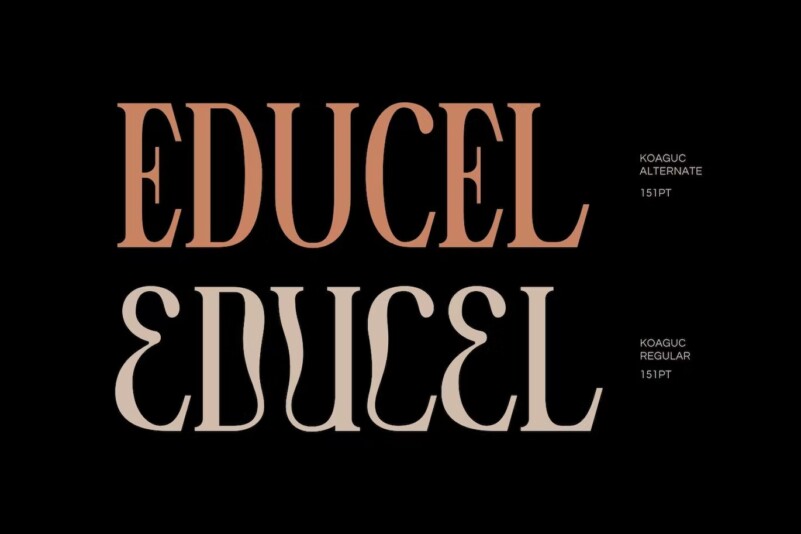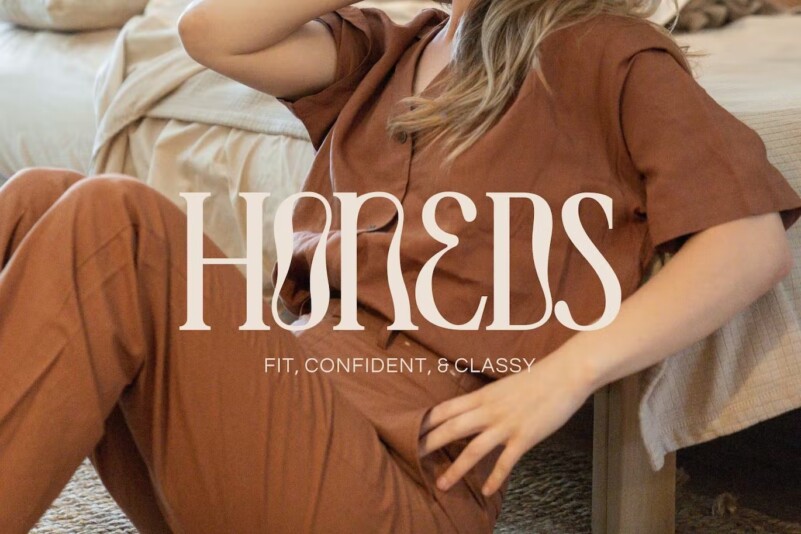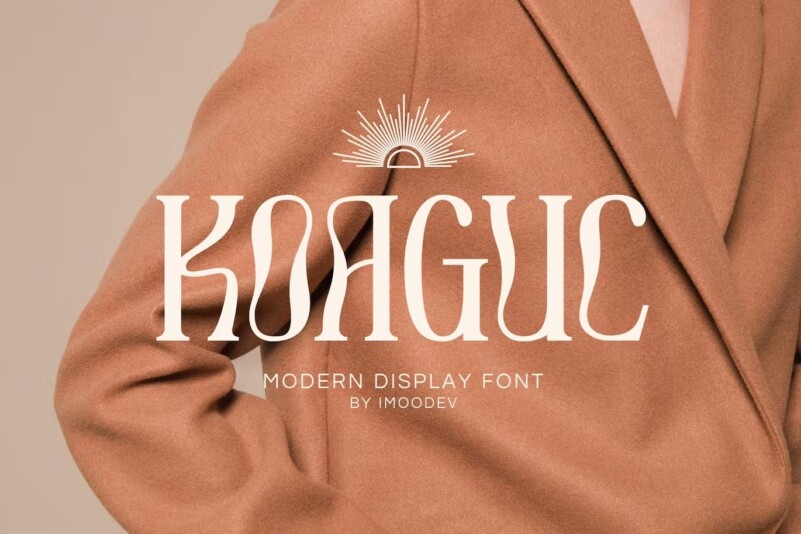
Koaguc – Beautiful Serif Fonts
Koaguc est de magnifiques Polices Serif empattement dotées d’une élégance visuelle, de courbes lisses et de belles ligatures claires, donnant à votre travail un aspect vrai et attrayant.
Une police polyvalente qui fonctionne à la fois dans les grandes et les petites tailles. Cette police convient à une grande variété de projets tels que les invitations, les logos, l’image de marque, les magazines, les photographies, les cartes, les emballages de produits, les tasses, les citations, les affiches, les étiquettes, les signatures, etc.
Police parfaite pour tous les secteurs d’activité, y compris les projets personnels, les studios, les Entreprise, les agences de création, l’industrie, les entreprises, etc.